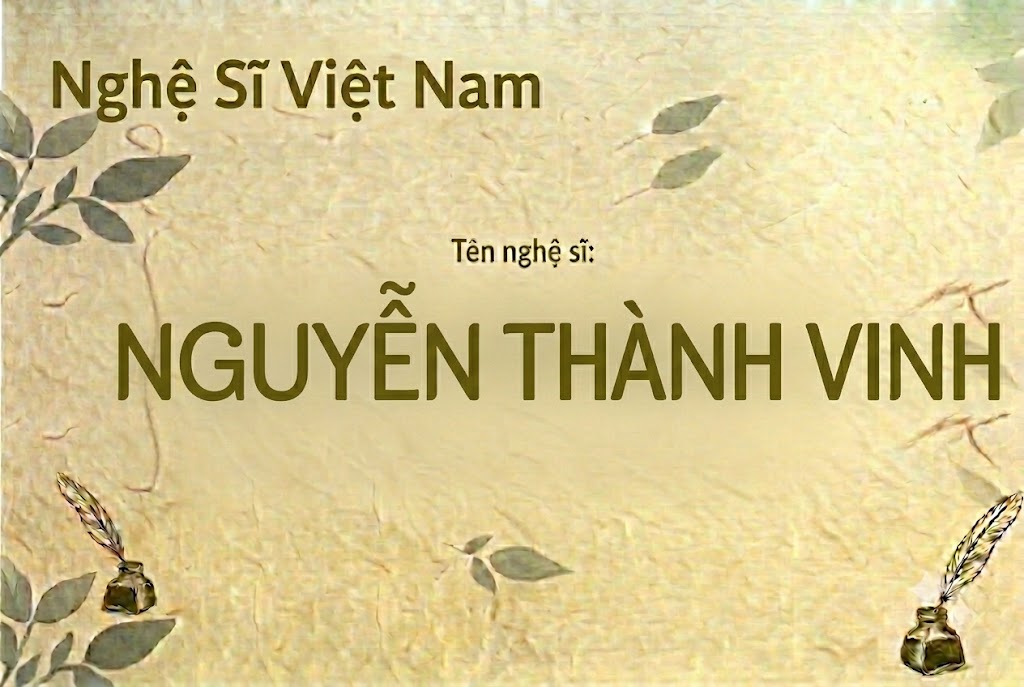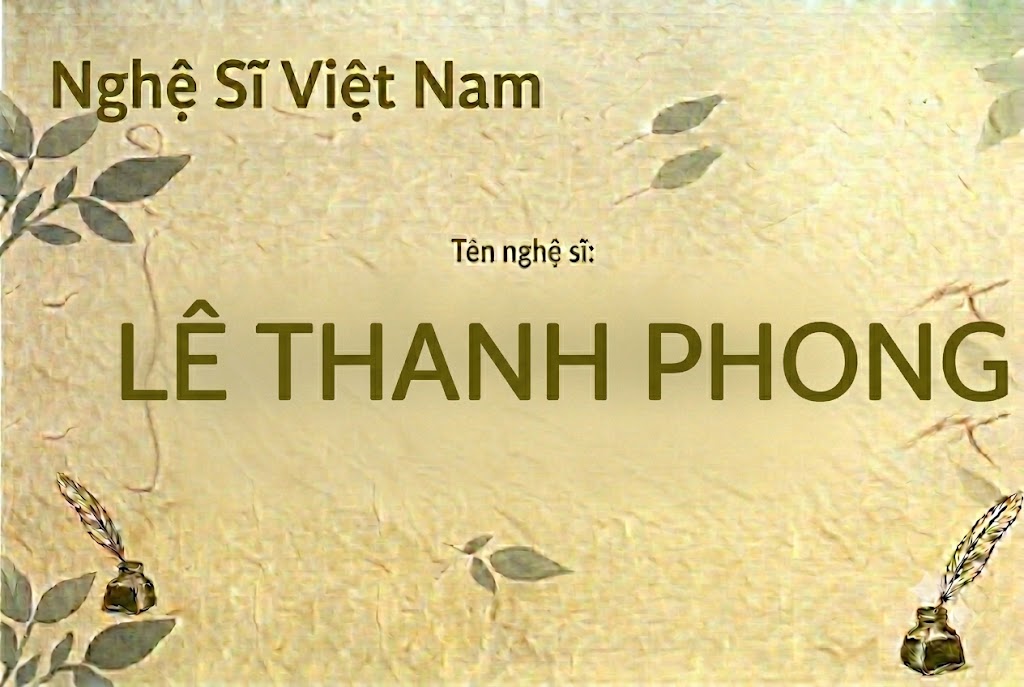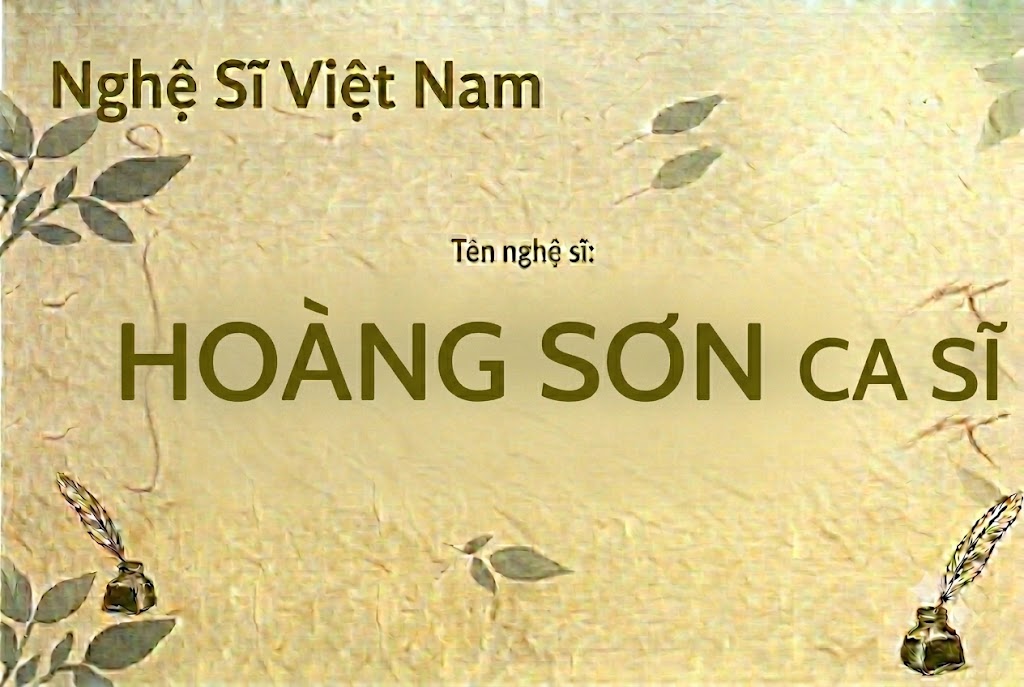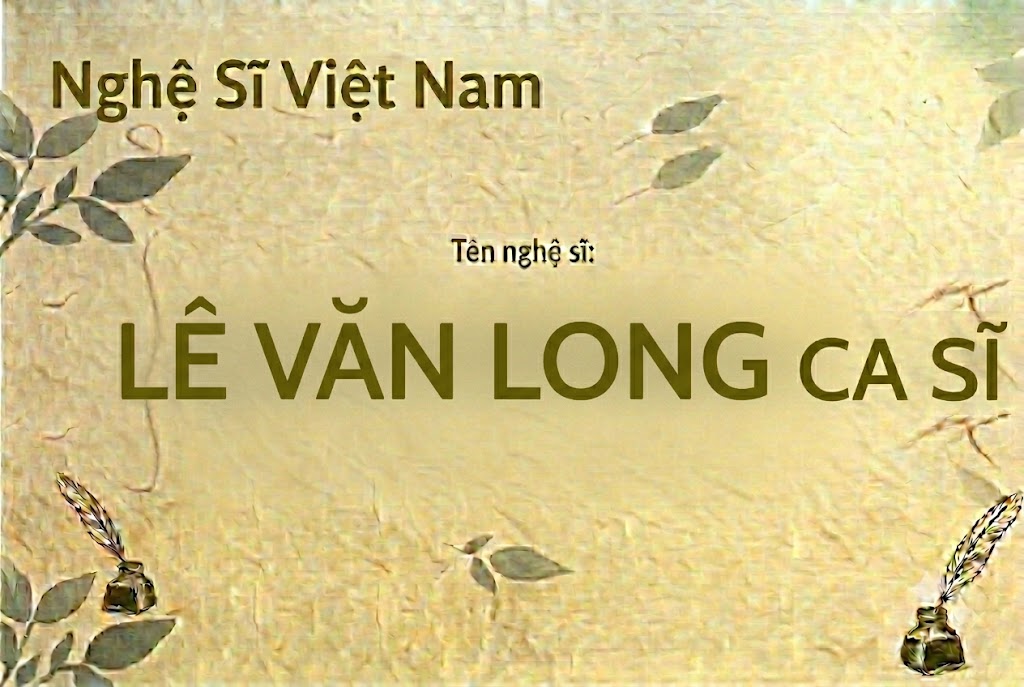
1FTV Cakelan
Trái ngược với các phông chữ siêu dày hầm hố, xu hướng thiết kế cao cấp luôn ưu tiên các kiểu chữ thanh mảnh, có chân sang trọng.
Những nét chữ tinh tế này giúp thổi hồn vào các thương hiệu thời trang, mỹ phẩm hoặc các ấn phẩm truyền thông mang tính nghệ thuật cao.
Nếu bạn đang tìm kiếm một phông chữ quý phái để làm nhận diện thương hiệu hay làm tiêu đề, thì font 1FTV Cakelan chính là sự lựa chọn tuyệt vời.
Giới thiệu về font 1FTV Cakelan
Font 1FTV Cakelan là một phông chữ display có chân (serif) mang phong cách sang trọng, cổ điển và đầy tính nghệ thuật.
Đặc điểm nổi bật của phong cách thiết kế Cakelan
Sức hút lớn nhất của font 1FTV Cakelan đến từ cấu trúc có chân cổ điển kết hợp cùng các nét chữ thanh mảnh, quý phái.
Cách tạo hình của bộ font này gợi liên tưởng đến các tạp chí thời trang danh tiếng, nơi sự tối giản và tính thẩm mỹ cao được đặt lên hàng đầu.
Phông chữ được xây dựng hoàn toàn theo cấu trúc all-caps (viết hoa toàn bộ), giúp tạo ra sự đồng đều và cân bằng tuyệt đối về mặt cao độ khi bạn sắp xếp dòng tiêu đề.
Khoảng hở giữa các nét chữ được tính toán vô cùng khoa học, giúp văn bản luôn giữ được sự thanh thoát, kiêu sa mà không bị rối mắt.
Để phông chữ vận hành mượt mà trên mọi hệ thống máy tính, phiên bản font 1FTV Cakelan đã trải qua quy trình xử lý thông số kĩ thuật kỹ lưỡng.
Hệ thống khoảng cách chữ (kerning) và độ giãn dòng (tracking) đã được căn chỉnh chuẩn xác, giúp các từ khi đứng cạnh nhau luôn giữ được khoảng trống thẩm mỹ tốt nhất.
Bên cạnh hệ thống chữ cái viết hoa đồng bộ, phông chữ còn tích hợp đầy đủ dãy số từ 0-9 cùng hệ thống các ký tự đặc biệt, dấu câu thông dụng (1234567890.:,;'"(!?) +-*/=).
Tiện ích này giúp bạn thoải mái sáng tạo các nội dung quảng cáo hay biên tập video tiếng Việt mà không lo gặp phải tình trạng lỗi hiển thị hay bị thiếu ký tự khi gõ.
Hình ảnh demo thực tế của font 1FTV Cakelan
Để giúp bạn dễ dàng hình dung khả năng co giãn và hiển thị linh hoạt của phông chữ này trên các kích thước khác nhau, hãy cùng xem qua bảng mô phỏng thực tế:
Kích thước nhỏ (12pt – 24pt): Các nét chữ mảnh và phần chân serif vẫn hiển thị rất rõ ràng, ngay ngắn, dễ đọc trên màn hình các thiết bị di động.
Kích thước lớn (36pt – 72pt): Đây là không gian lý tưởng để font chữ phô diễn toàn bộ vẻ đẹp quý phái, tạo hiệu ứng thị giác sang trọng và đẳng cấp cho các tiêu đề chính.
Ứng dụng của font Cakelan trong thiết kế đồ họa và làm video
Sở hữu nét cá tính quý phái và phom dáng serif thanh lịch, font 1FTV Cakelan mở ra không gian ứng dụng rộng lớn cho các dự án truyền thông:
Thiết kế bìa tạp chí và poster thời trang: Hoàn hảo cho các ấn phẩm về thời trang, mỹ phẩm, trang sức cao cấp hoặc các sự kiện triển lãm nghệ thuật.
Làm tiêu đề video ngắn nghệ thuật (Tiktok, Shorts, Reels): Kiểu chữ thanh mảnh này rất thích hợp để làm các cụm từ tiêu đề mở đầu video phong cách nhẹ nhàng, sâu lắng, giúp giữ chân người xem lướt chậm lại.
Banner nhà hàng cao cấp và thiệp mời sự kiện: Cực kỳ lý tưởng để thiết kế menu, bảng hiệu cho các nhà hàng châu Âu, tiệm hoa, spa hoặc làm thiệp cưới phong cách tối giản, sang trọng.
Nhận diện thương hiệu phong cách luxury: Phù hợp làm logo dạng chữ, biểu ngữ quảng cáo hoặc thiết kế nhãn mác cho các thương hiệu cần sự tinh tế, đại diện cho phân khúc cao cấp.